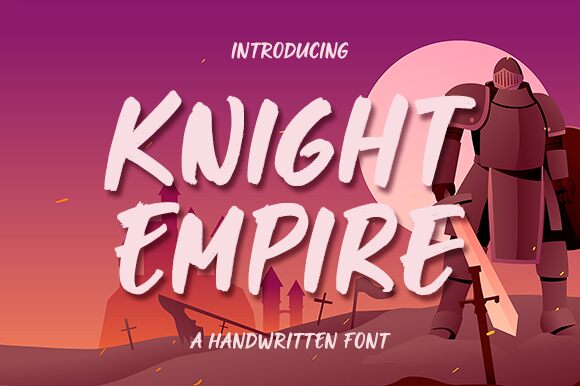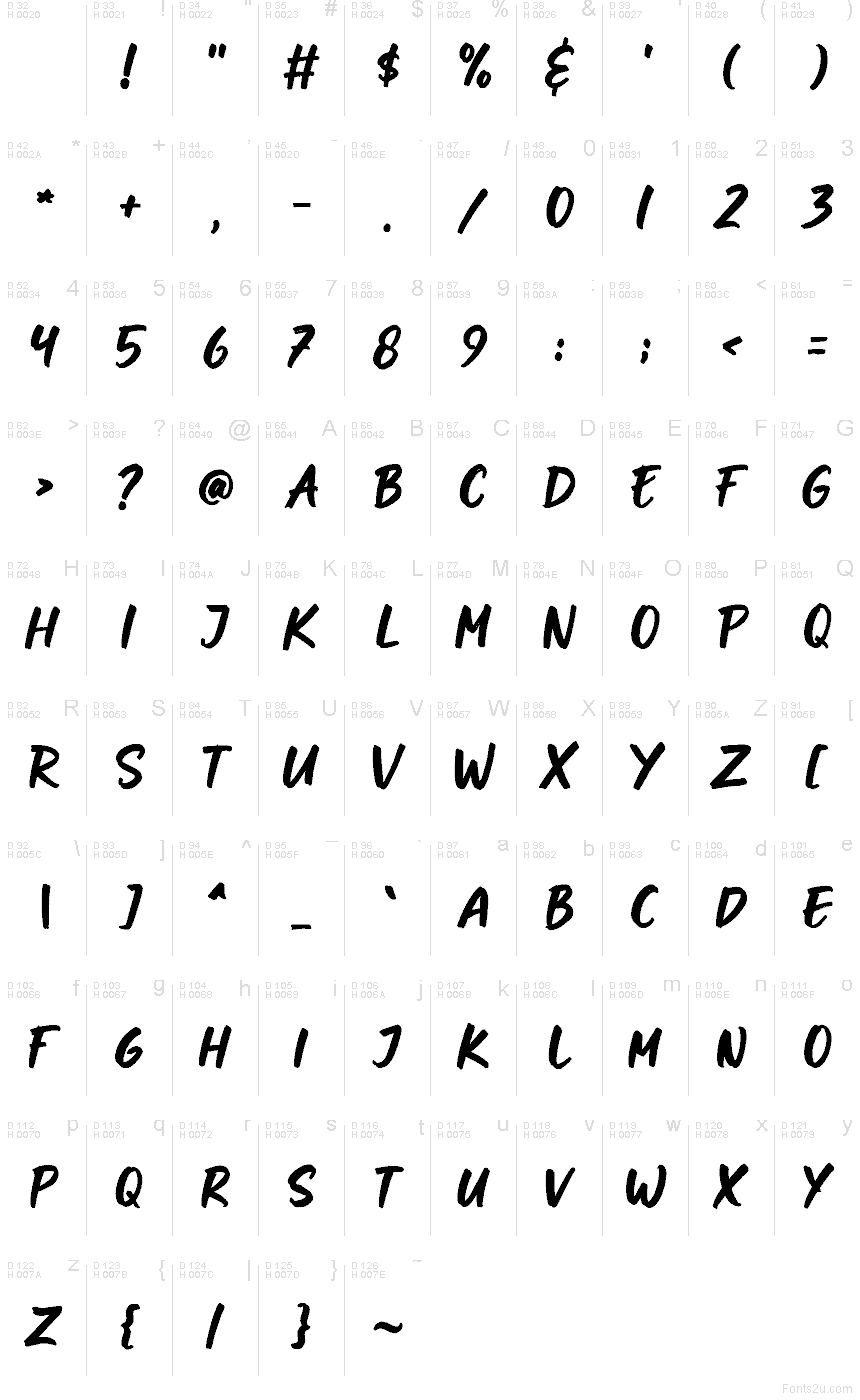
Knight Empire od Graphix Line Studio je bezplatné štětcové nadpisové písmo s údernými, ručně malovanými kapitálkami. Jeho široké tahy náhle mění šířku a zanechávají tupé okraje, špičaté spoje a drsné stahy, které si zachovávají stopu nabitého štětce. Písmena se na některých místech naklánějí dopředu.
Zvláště přesvědčivé je pro titulní obrazovky akčních her, kde prudké tvary evokují rychlost a boj. Stejná přímost se hodí pro plakáty bojových umění, sportovní merchandising a obaly alb postavené na agresivní fotografii. V těchto souvislostech mohou opakované tahy štětcem fungovat jako malované stopy po dopadu a spojovat slova s pohybem v okolní grafice.